디자인에서 폰트는 톤 & 매너, 핵심 키워드 강조, 본문의 가독성 등 중요한 요소 중 하나입니다.
이 포스팅에서는 저작권 없는 상업용 무료 폰트를 사용하고 다운로드할 수 있는 사이트를 알려드리겠습니다.
상업용 무료 폰트 – 한글
1. 눈누 폰트
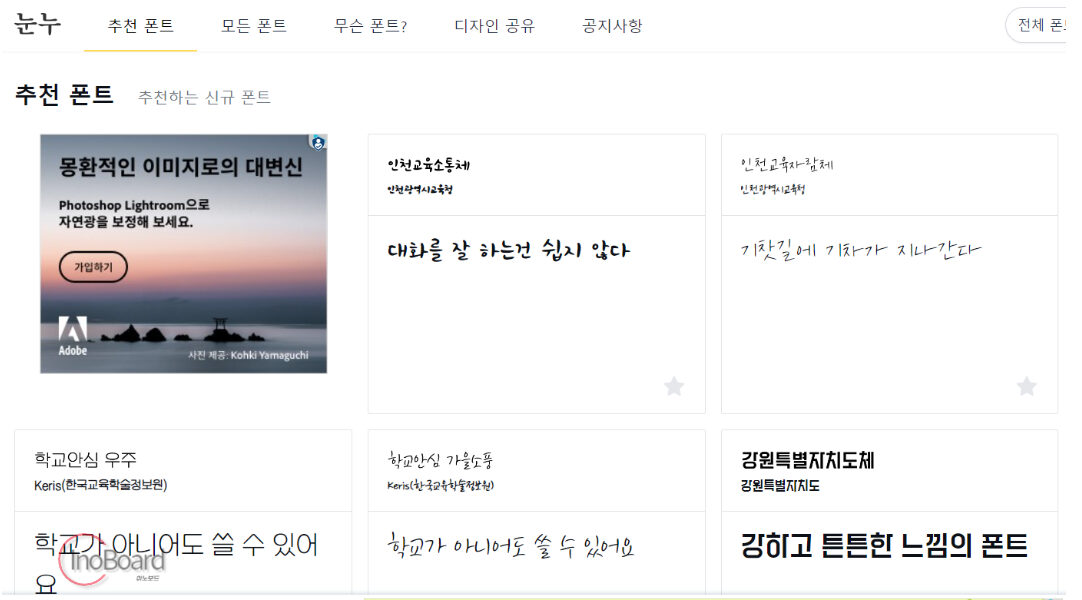
눈누 폰트는 상업적으로 사용할 수 있는 한글 무료 폰트 다운로드 및 공유 사이트입니다.
원하는 단어나 문장으로 미리보기를 통해 글씨체를 확인할 수 있으며, 폰트의 허용 범위나 형태를 쉽게 필터링하면서 확인할 수 있습니다.
깔끔한 글씨체, 손 글씨체 폰트 등 다양한 서체를 다운로드할 수 있습니다.
- 한글뿐만 아니라 영문과 숫자를 포함한 다양한 글자체 제공
- 필터를 사용해서 고딕, 명조, 손글씨 등 원하는 폰트를 쉽게 검색
- 깔끔한 글씨체, 손 글씨체 폰트 등 예쁜 한글 폰트가 많음
2. 구글 폰트
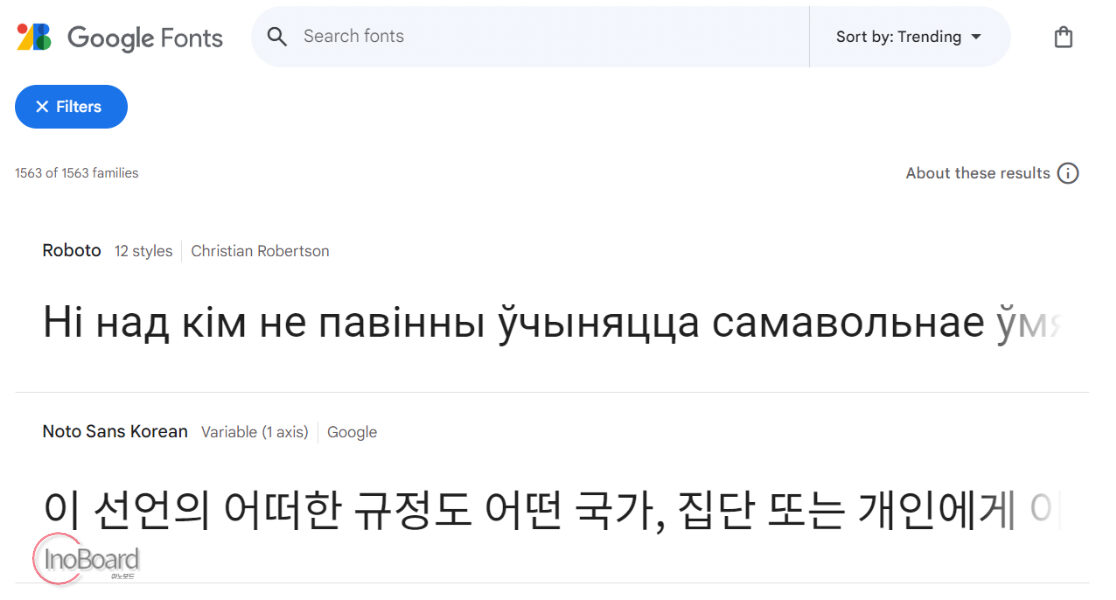
구글 폰트는 저작권 걱정 없는 글꼴 라이브러리 사이트입니다.
대부분의 언어를 지원하며, 1,000개에 가까운 폰트를 제공하고 있습니다.
이미 많은 디자이너와 직장인, 대학생 등 많은 사용자로부터 인기를 얻고 있는 다양한 글꼴을 제공합니다.
- 필터를 이용해 한글, 영어 및 기타 언어의 폰트를 쉽게 검색 가능
: 한국어 폰트의 경우 31개 폰트를 제공 - 마음에 드는 폰트를 클릭하여 원하는 문구 입력 후 미리 보기 제공
3. 네이버 클로바 – 나눔 손글씨 글꼴
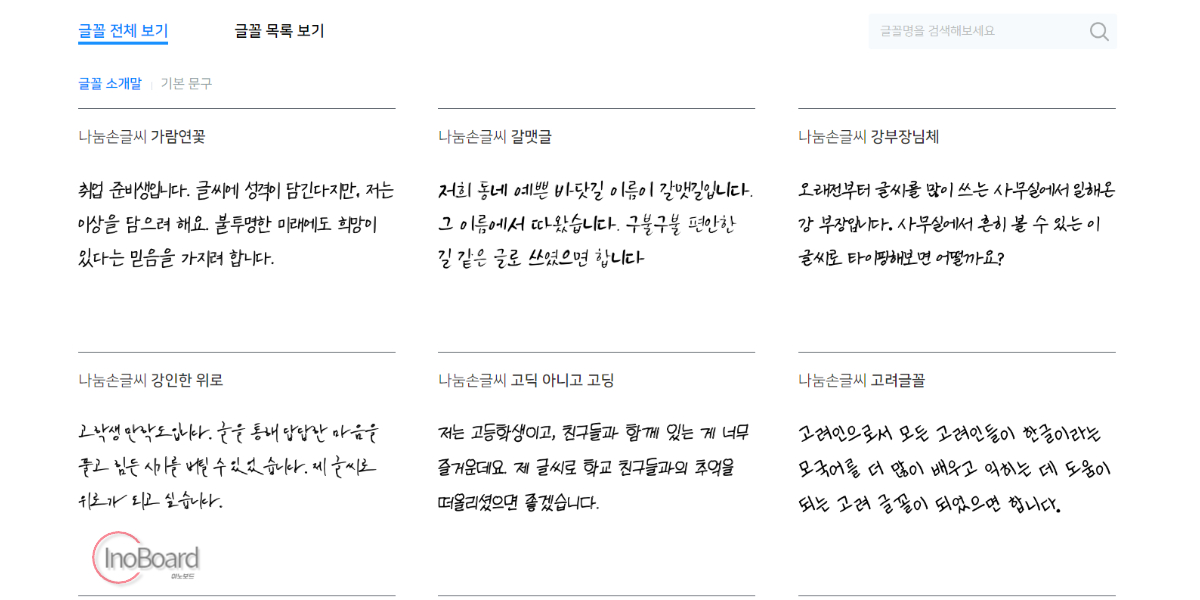
많이 알려진 유명한 폰트 또는 격식 있는 글꼴 이외에 특별한 손 글씨체 폰트를 찾고 있다면, 네이버 클로바 무료 폰트 “나눔 손글씨 글꼴”을 추천해 드립니다.
한글날 손글씨 공모전에 참여한 시민들의 손글씨에 AI 기술을 접목하여 손 글씨체 폰트를 제공합니다.
- 109종의 손 글씨체 폰트 제공
- 손으로 쓴 것과 같은 느낌을 주는 글씨체가 많아 다양한 곳에 사용 가능
4. 공유마당
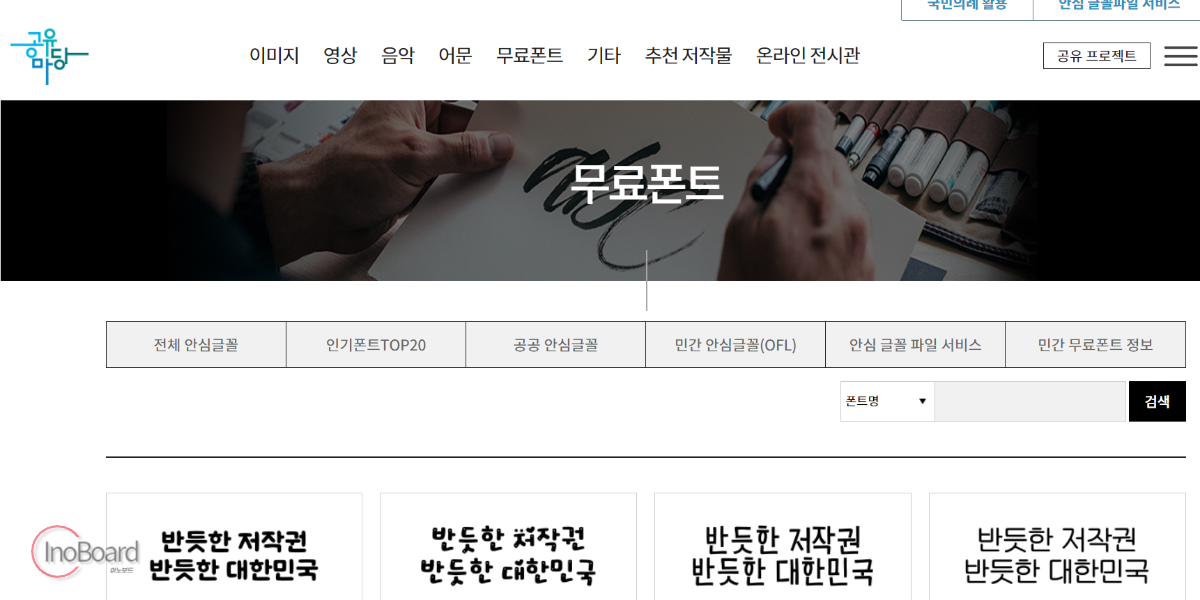
공유마당은 한국저작권위원회에서 운영하는 무료 저작물 사이트입니다.
폰트를 포함하여 미술, 사진, 영상, 음악, 라이선스 등 다양한 저작물을 제공합니다.
- 폰트뿐만 아니라 이미지, 영상, 음악 등 다양한 디자인 리소스다운 가능
- 한글 베이스의 폰트 사이트
상업용 무료 폰트 – 영어
1. Dafont
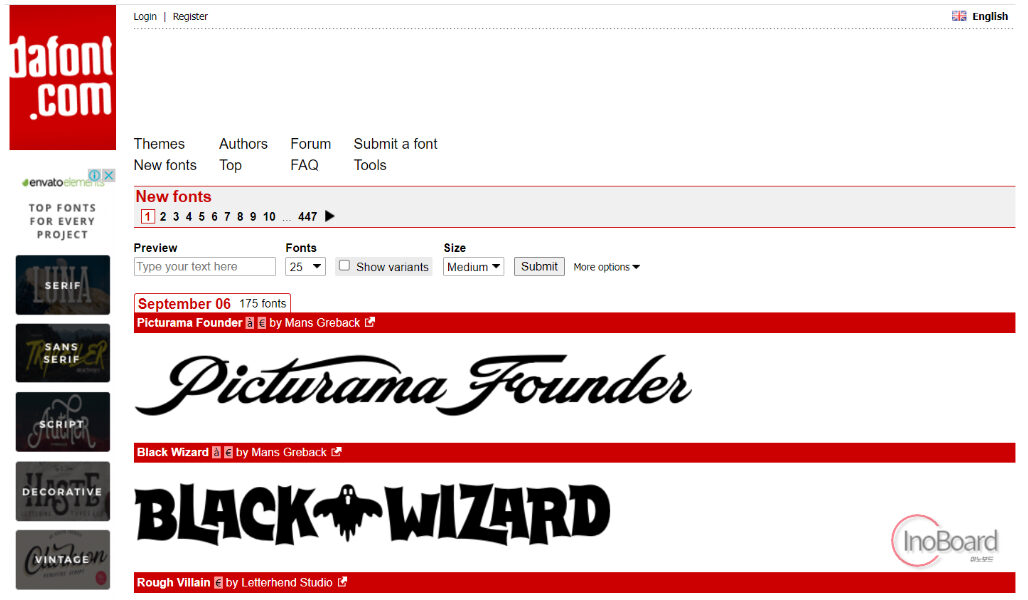
Dafont는 가장 오래되고 많은 사람이 이용하는 영어 폰트 사이트입니다.
이 사이트에는 거의 6만 개 이상의 폰트를 제공하고 있습니다.
폰트의 종류가 워낙 많기 때문에 카테고리, 테마도 다양하게 분류되어 있습니다.
2. Font Squirrel
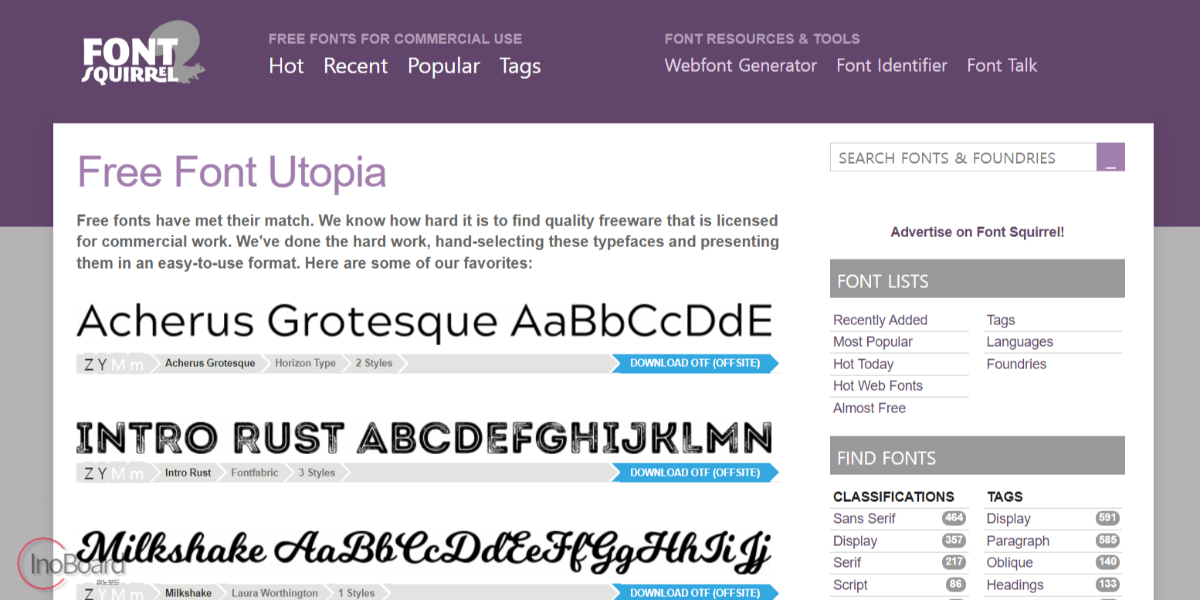
Font Squirrel은 100% 상업적으로 이용할 수 있는 폰트를 모아 놓은 사이트입니다.
다른 사이트와 약간 다른 점은 Font Squirrel 사이트에서 폰트를 바로 다운받을 수 있는 것이 아니라, 다른 웹 사이트에서 무료로 제공하는 폰트의 정보를 한곳에 모아 놓은 사이트라고 보시면 됩니다.
- 폰트 매칭 도구를 이용해 유사한 폰트 찾기 가능
- 원하는 폰트 클릭 시 해당 폰트의 원작자 소스로 이동하는 링크 제공
3. FontSpace
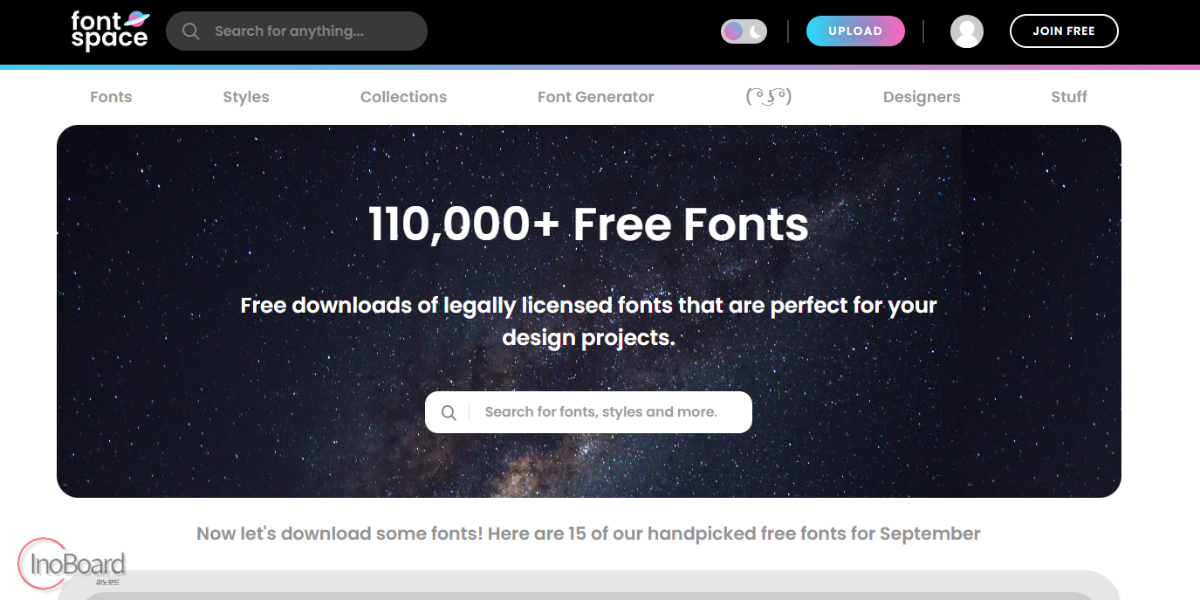
FontSpace는 약 110,000개 이상의 무료 폰트를 모아 놓은 사이트입니다.
깔끔한 인터페이스로 구성되어 있고, 미리 보기 기능도 지원하기 때문에 내가 다운받으려는 폰트의 적용 모습을 쉽게 확인해볼 수 있습니다.
- 각 폰트에 대해 미리 보기 기능을 제공하여 다운로드 전 미리 확인 가능